Fincker Font Cuisine: Neue Typefoundry von Julien Fincker
Nach rund sechs Jahren der freien Schriftgestaltung startet Julien Fincker jetzt seine eigene Typefoundry. Unter dem Namen »Fincker Font Cuisine« sind ab sofort die Schriften des Typedesigners zu finden – unter anderem auch die neue »Nestor«.
Fincker zieht Parallelen zwischen dem Kochen und dem Gestalten von Schriften. Für ihn sind es die Details, die den entscheidenden Unterschied ausmachen – ein Gedanke, der sich auch im Namen Font Cuisine widerspiegelt.
Ein besonderer Fokus liegt auch auf dem Branding der Foundry, das von der Geschichte der Familie Fincker inspiriert ist. Die Vorfahren des Designers führten eine Feinkostmetzgerei in Colmar, Frankreich, die bis in die 1950er Jahre existierte. Damals schuf der Künstler Jean-Jacques Waltz, auch bekannt als „Hansi“, ein ikonisches Logo mit der Silhouette von Juliens Urgroßvater und dessen Bruder. Diese historische Bildmarke ist bis heute auf dem ehemaligen Geschäftshaus der Familie zu sehen und wurde für Finckers Foundry modernisiert und weitergeführt.
Auch der Name Font Cuisine bezieht sich auf dieses familiäre Erbe. So erinnert die Abkürzung »F.F.C.« an das ursprüngliche »Fincker Frères Colmar«. In der neuen Typefoundry wird dieses Erbe in einem modernen, typografischen Kontext weitergeführt.
Julien Fincker hat seine Liebe zur Schrift in den letzten Jahren vertieft. Nachdem er als Diplom-Kommunikationsdesigner unter anderem im Grafischen Atelier Stankowski + Duschek tätig war, begann er im Jahr 2018, eigene Buchstaben zu gestalten. Seitdem hat er verschiedene Schriften entwickelt und möchte sich nun voll auf seine Typefoundry »Font Cuisine« konzentrieren, mit der er sich der Typografie im vollen Umfang widmen möchte.
Neue Schriftfamilie »Nestor«
Mehr Informationen gibt es auf der Website der Foundry. Dort findet man neben Schriften wie Grantig, Royalis oder Spitzkant auch die neue Nestor. Die Schriftfamilie zeichnet sich durch ihre weichen, abgerundeten Ecken und schmale Form aus. Diese Kombination verleiht ihr einen aufrechten, kompakten und selbstbewussten Charakter.
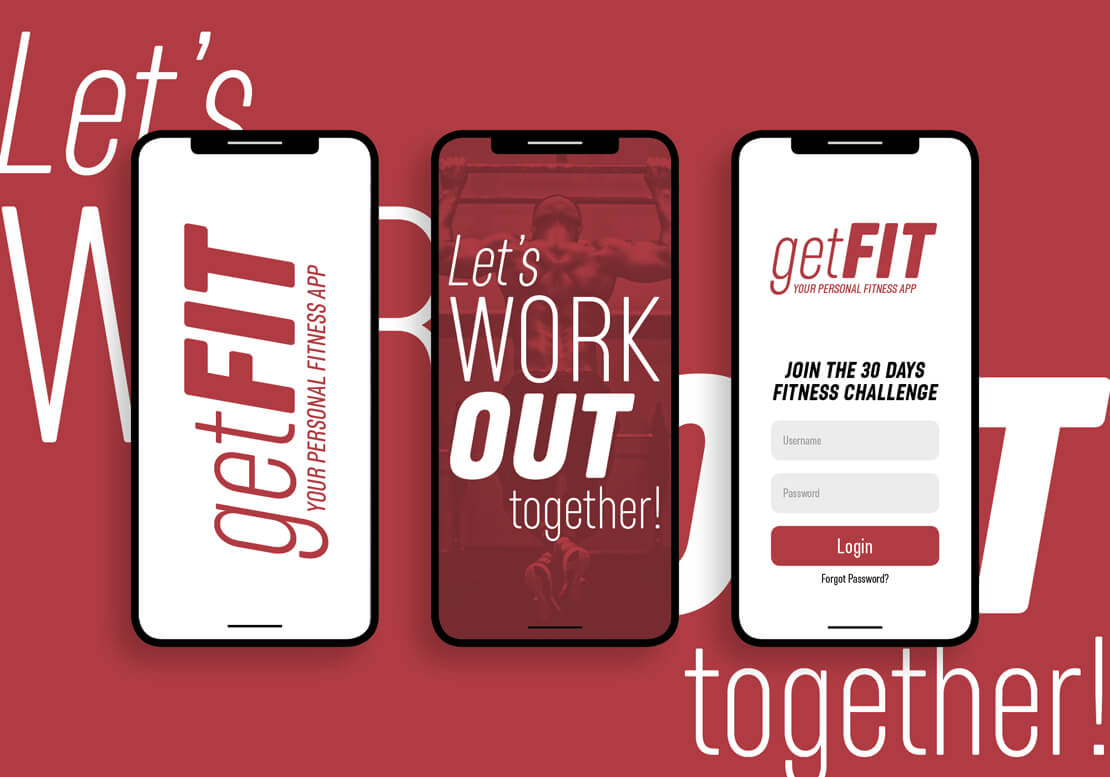
Mit ihren klaren, geschlossenen Formen wirkt sie prägnant und deutlich, was sie unter anderem für den Einsatz in Headlines, Editorials, Verpackungsdesign, Branding und Werbeanwendungen eignet.
Die Nestor-Schriftfamilie verfügt über insgesamt 12 Schnitte, die von »Extralight« bis »Extrabold« reichen und außerdem entsprechende Kursive bieten. Sie verfügt dabei über eine ganze Reihe OpenType-Features wie zum Beispiel alternative Zeichen als Stylistic Sets, automatische Brüche, Pfeile und mehr.